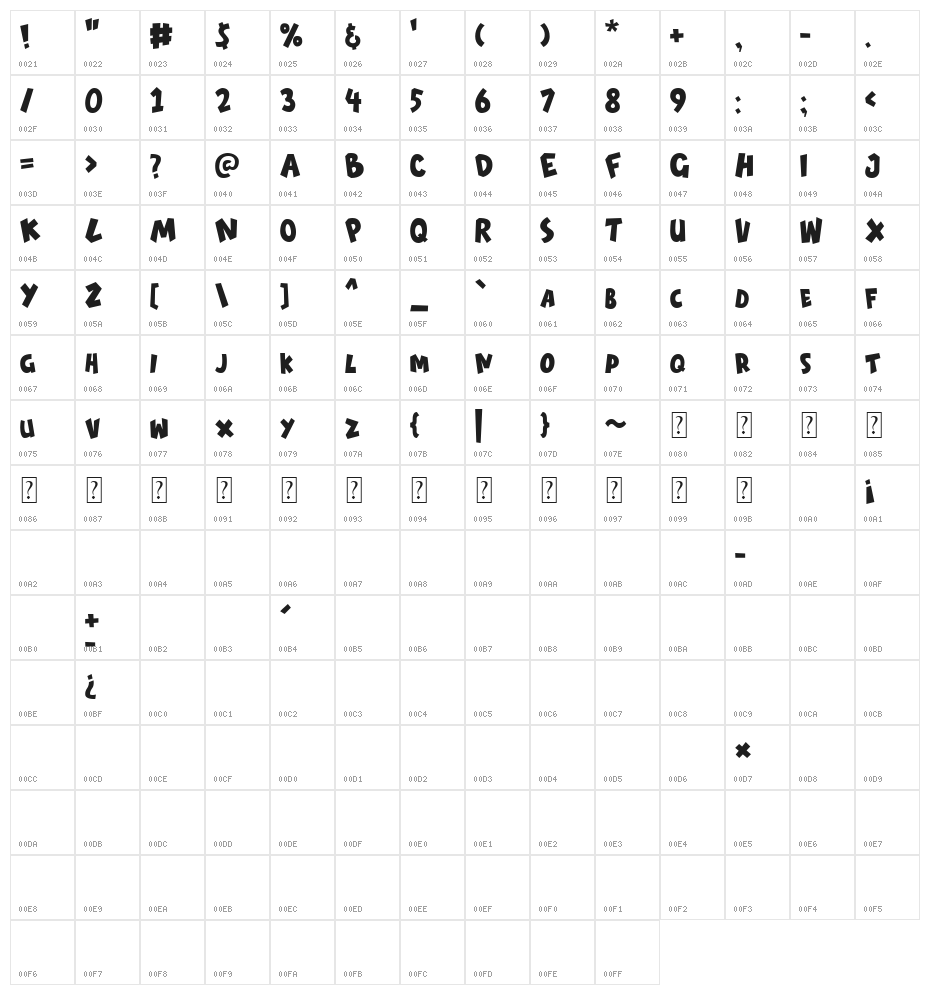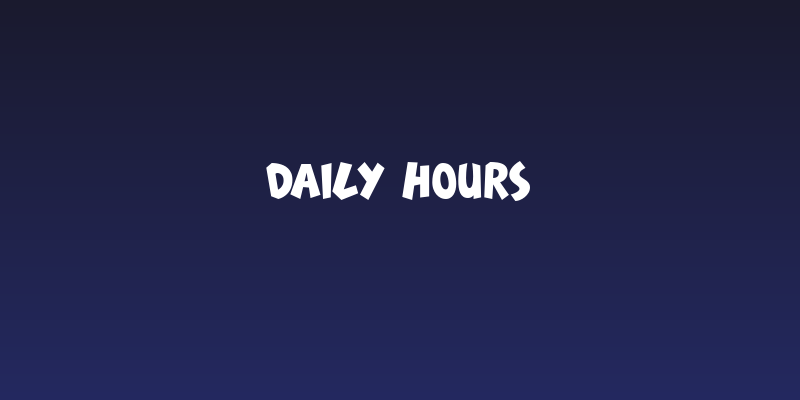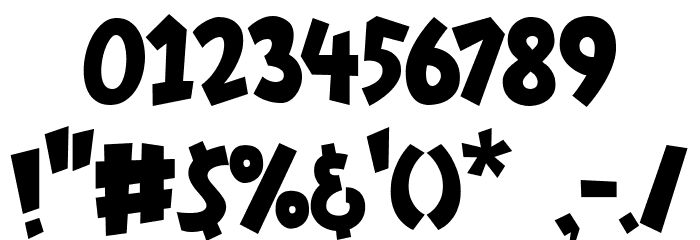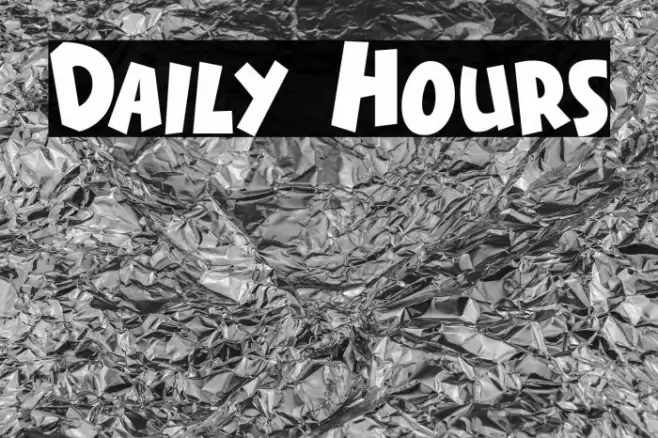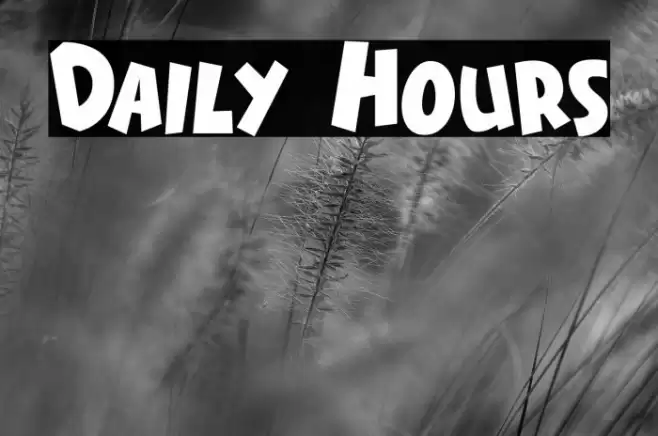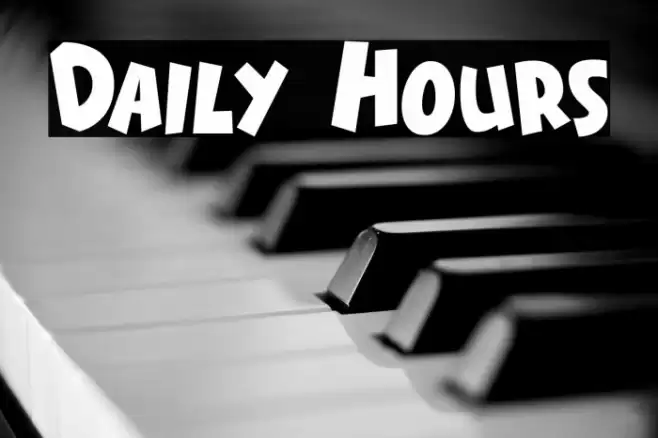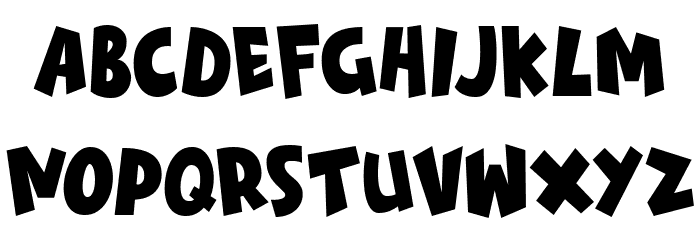
Daily Hours Font
✎ Cartoon
| Gesamtstil | Playful, Whimsical |
| Anwendungsfall | Headlines, Posters, Branding |
| Vorgeschlagene Projekte | Ideal for children's books, comic strips, playful branding, and event posters. |